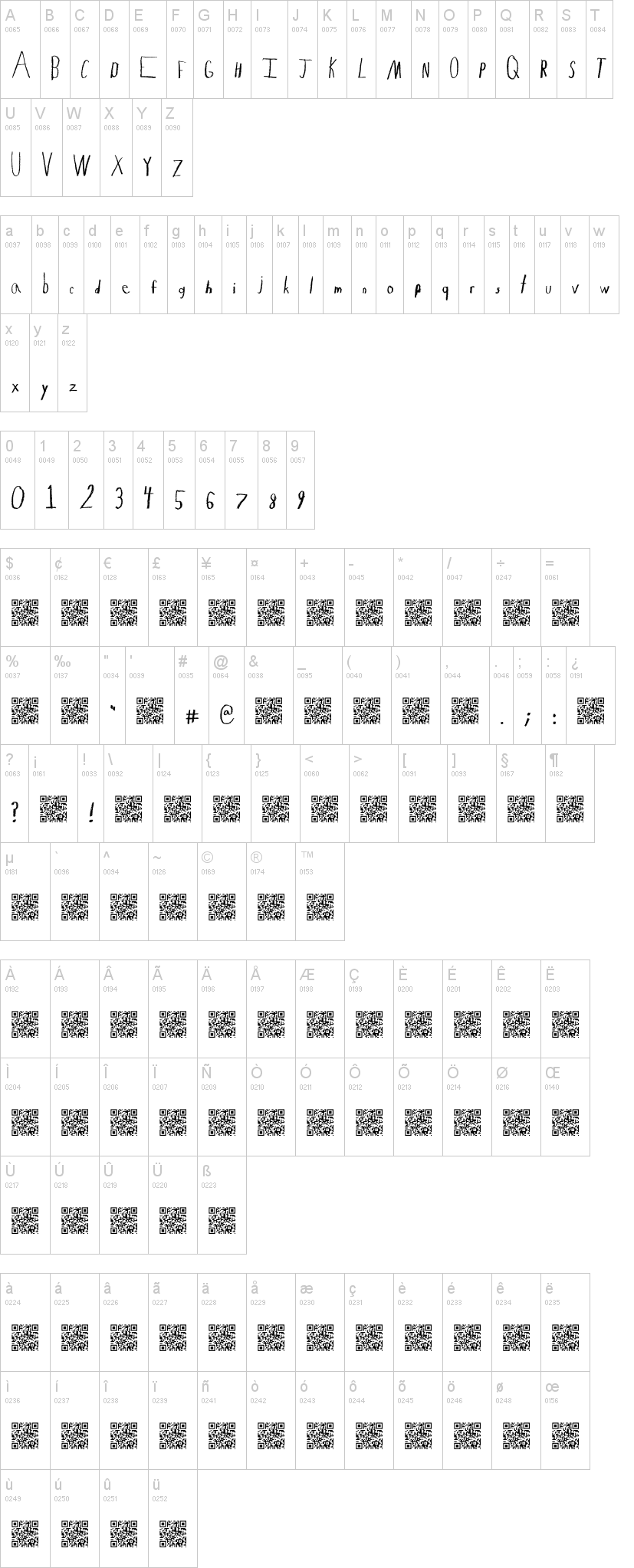
Lemonade Hustler
Lemonade Hustler 是一款自由字体,由一位美国设计师Alesia Kazakova创作。它具有细腻的线条,简洁的字母和活泼的外观,适合用于品牌标识、海报、海报、T恤和其他印刷品的设计。它的灵感来源于拼贴艺术,拥有活泼的色彩和线条,更具有创意。 Lemonade Hustler 字体具有良好的可读性,可以帮助您在设计中轻松添加一点活力。
Lemonade Hustler是一款非常不错的手写艺术字体,具有很好的视觉感,适合于文化类的宣传设计、商业类品牌的广告和产品包装设计以及个性化文字排版等较多场景。